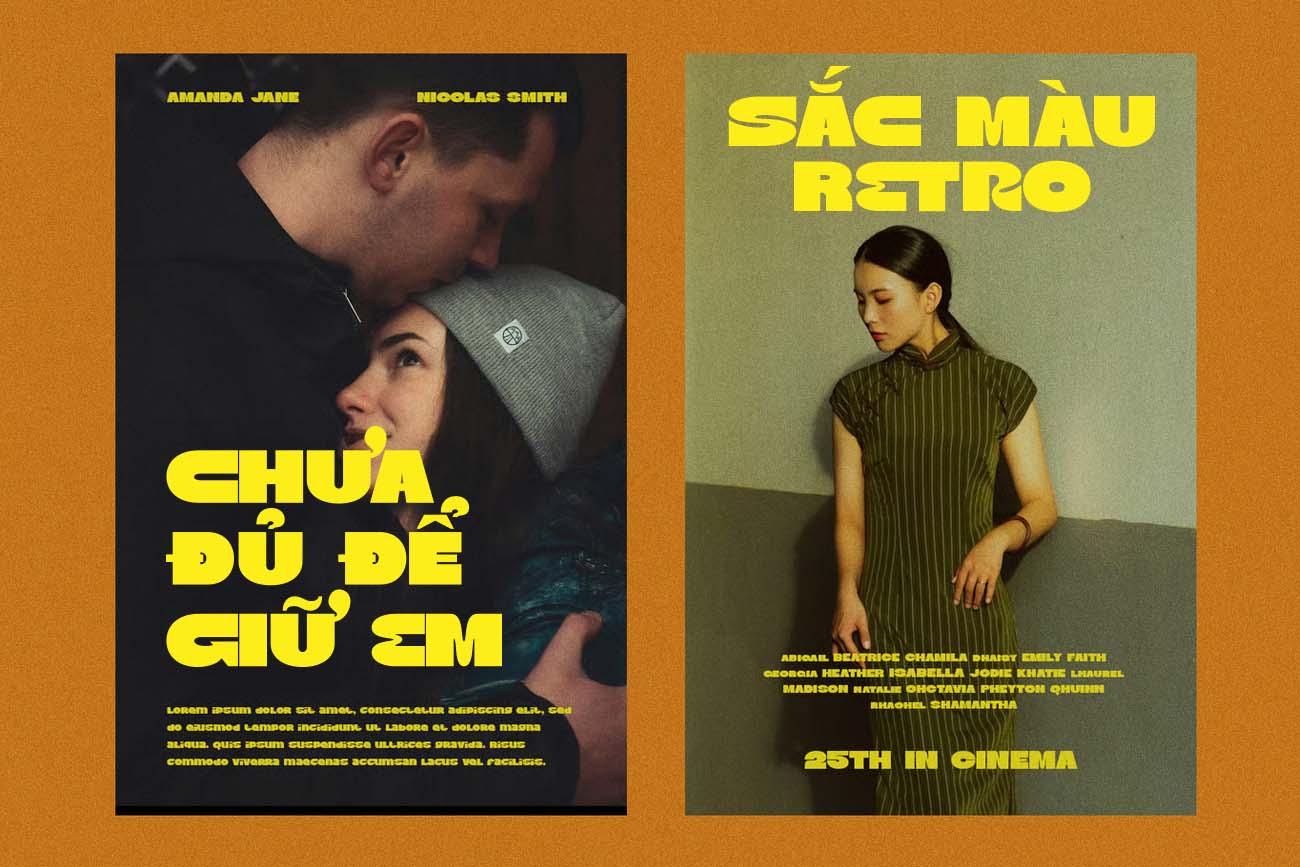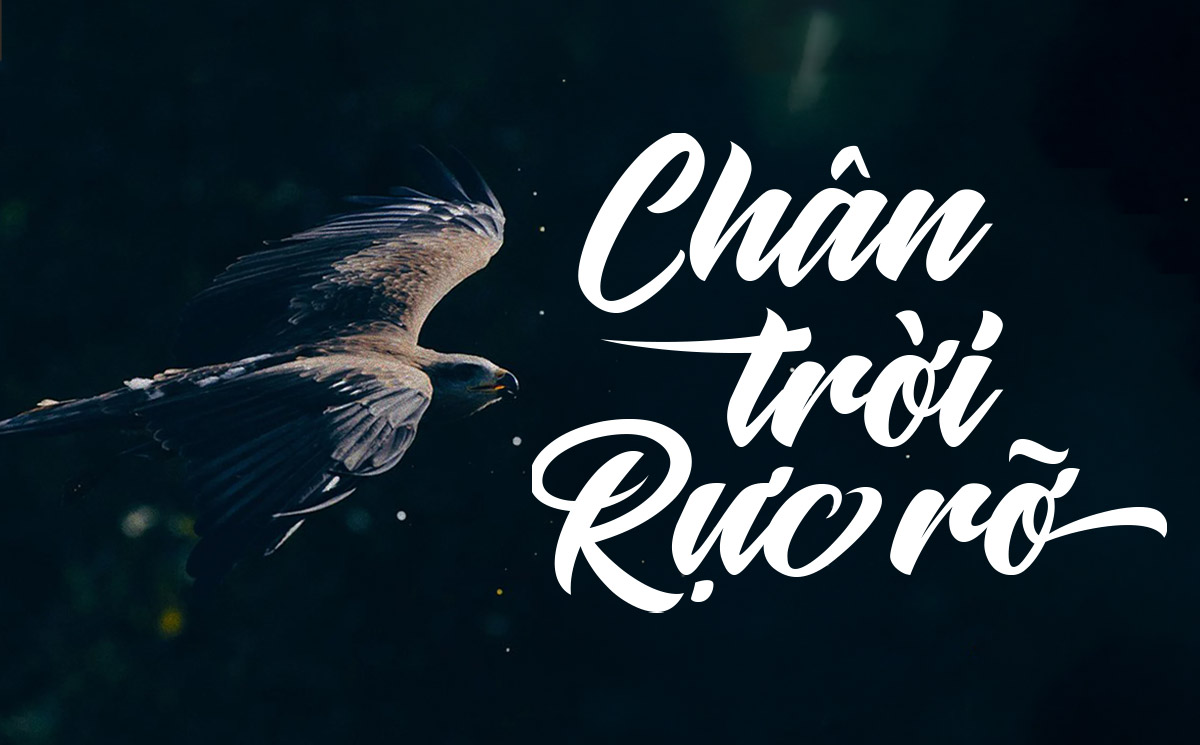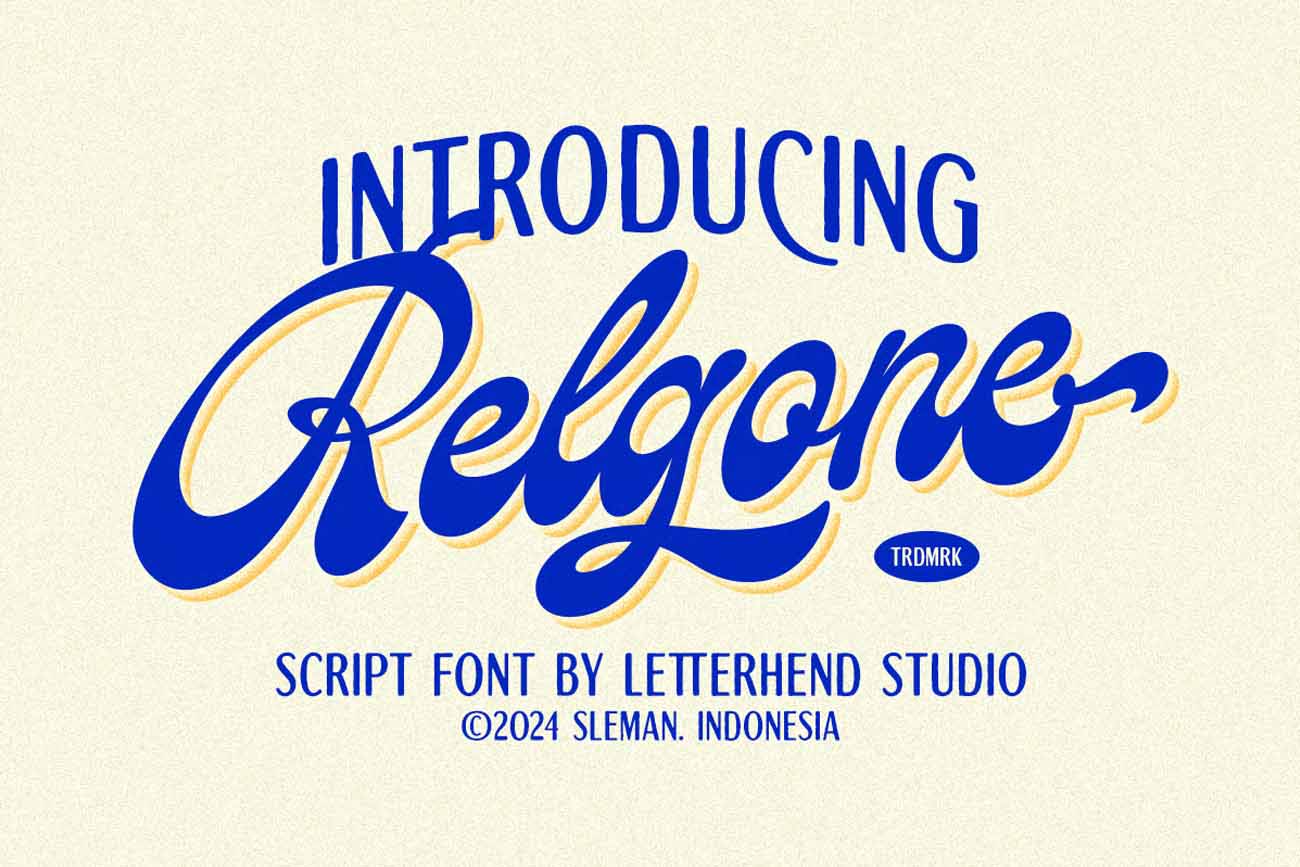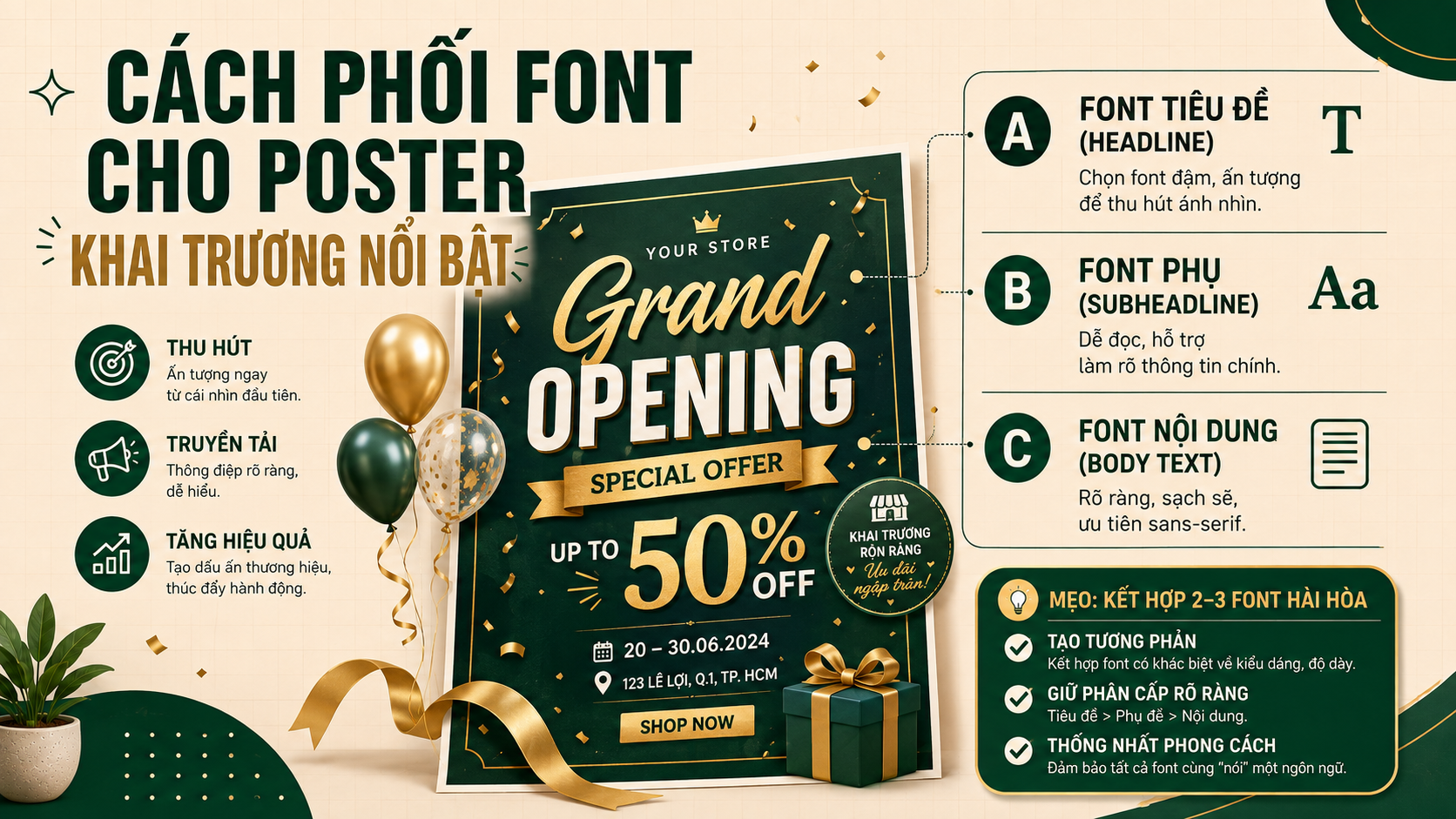
Font chữ cho sự kiện khai trương, grand opening và poster ưu đãi
Gợi ý 15 font TH Việt hóa nổi bật cho poster khai trương, grand opening, ưu đãi mở bán, banner sale opening và social post.
Poster khai trương cần tạo cảm giác “đang có chuyện vui diễn ra” ngay từ vài giây đầu. Khác với proposal hay catalogue, font cho grand opening không nhất thiết phải quá trung tính. Nó cần nổi bật, có khí thế, dễ đọc khi đặt trên nền đỏ, vàng, ảnh cửa hàng, ảnh sản phẩm hoặc các mảng ưu đãi lớn như “Mua 1 tặng 1”, “Giảm 50%”, “Tuần lễ khai trương”.
Bài viết này gợi ý 15 font TH Việt hóa khác nhóm font tài liệu doanh nghiệp gần đây, tập trung vào display, retro, brush, script và hoạt hình. Các font này phù hợp cho poster khai trương, banner grand opening, bài đăng social, backdrop sự kiện, biển treo cửa hàng và chương trình ưu đãi mở bán.
Chọn font khai trương cần chú ý gì?
Font khai trương phải làm tốt ba việc: thu hút, đọc nhanh và đúng không khí thương hiệu. Nếu cửa hàng là cafe retro, font hoài cổ sẽ hợp hơn font công nghệ. Nếu là showroom, gym hoặc cửa hàng thiết bị, font cứng cáp sẽ tạo cảm giác mạnh hơn. Nếu là tiệm bánh, trà sữa, kid shop, font tròn vui sẽ khiến poster dễ thương và gần gũi hơn.
Top font TH cho poster khai trương, grand opening và ưu đãi mở bán
1. TH Roge - poster grand opening kiểu retro, headline “Khai trương” và banner cửa hàng có cá tính
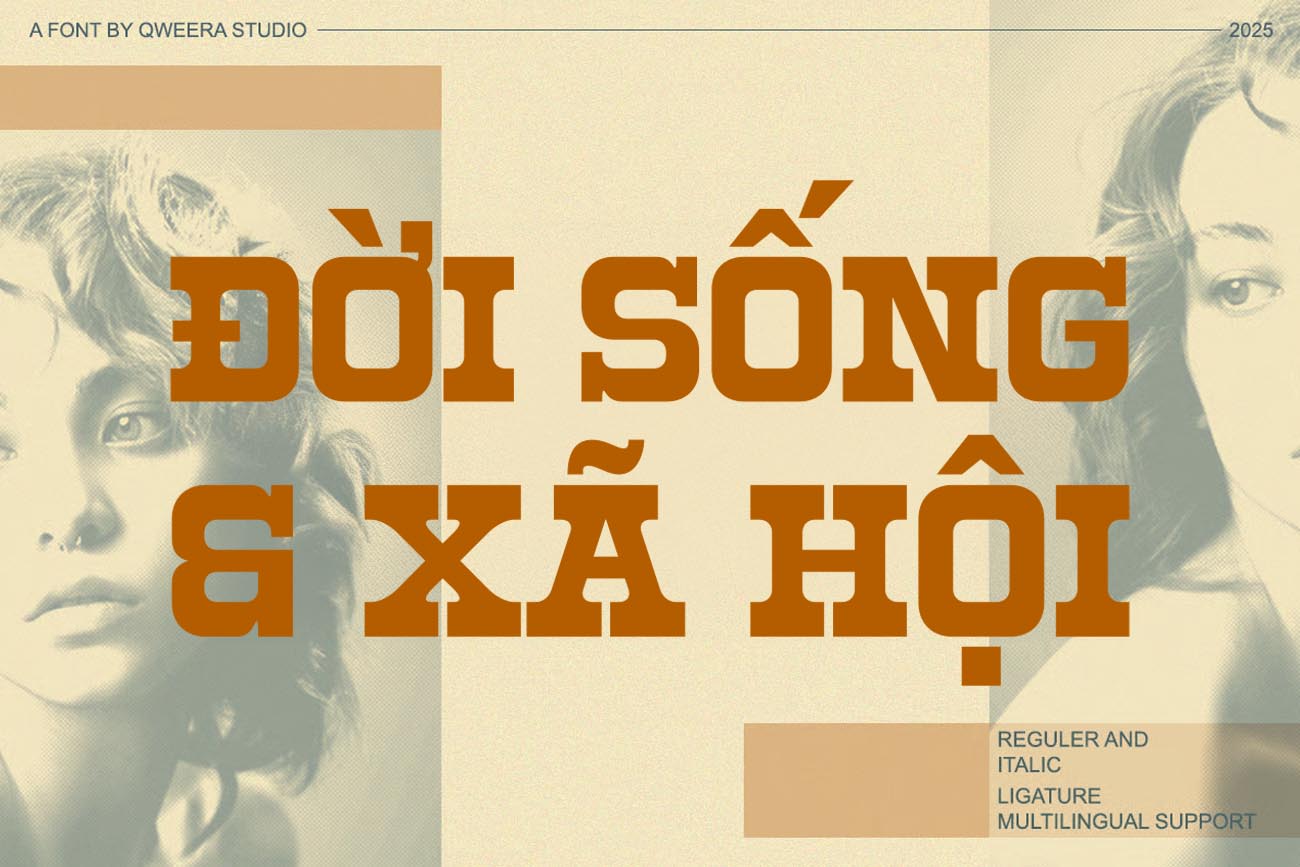
Tải font TH Roge nếu anh đang làm poster grand opening kiểu retro, headline “Khai trương” và banner cửa hàng có cá tính. Điểm mạnh của TH Roge là display retro nổi bật, dễ tạo cảm giác sự kiện có không khí và đáng ghé. Với poster khai trương, font này nên được thử trước trên các cụm chữ thật như “Khai trương hồng phát”, “Grand Opening”, “Ưu đãi mở bán”, “Giảm đến 50%” hoặc “Quà tặng 3 ngày đầu”.
Khi dùng TH Roge, anh nên giữ headline ngắn và mạnh. Các thông tin phụ như địa chỉ, thời gian, điều kiện ưu đãi, hotline nên dùng font sans-serif dễ đọc hơn để khách hàng không bỏ sót chi tiết quan trọng.
2. TH Acttime - poster ưu đãi mở bán, banner sale lớn và countdown khai trương
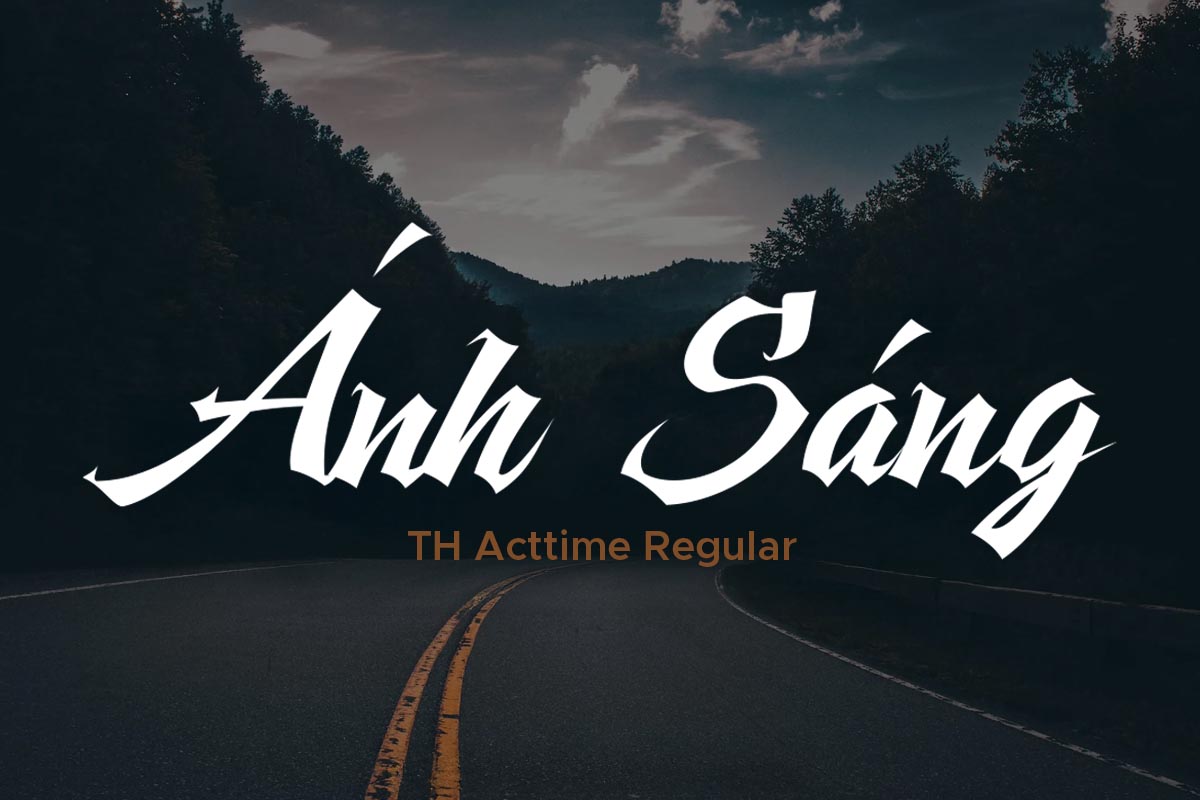
Tải font TH Acttime nếu anh đang làm poster ưu đãi mở bán, banner sale lớn và countdown khai trương. Điểm mạnh của TH Acttime là nét đậm, khỏe, giúp thông điệp giảm giá nhìn có lực hơn. Với poster khai trương, font này nên được thử trước trên các cụm chữ thật như “Khai trương hồng phát”, “Grand Opening”, “Ưu đãi mở bán”, “Giảm đến 50%” hoặc “Quà tặng 3 ngày đầu”.
Khi dùng TH Acttime, anh nên giữ headline ngắn và mạnh. Các thông tin phụ như địa chỉ, thời gian, điều kiện ưu đãi, hotline nên dùng font sans-serif dễ đọc hơn để khách hàng không bỏ sót chi tiết quan trọng.
3. TH Throwback Glorious - thiết kế khai trương phong cách vintage, poster quán cafe và shop lifestyle
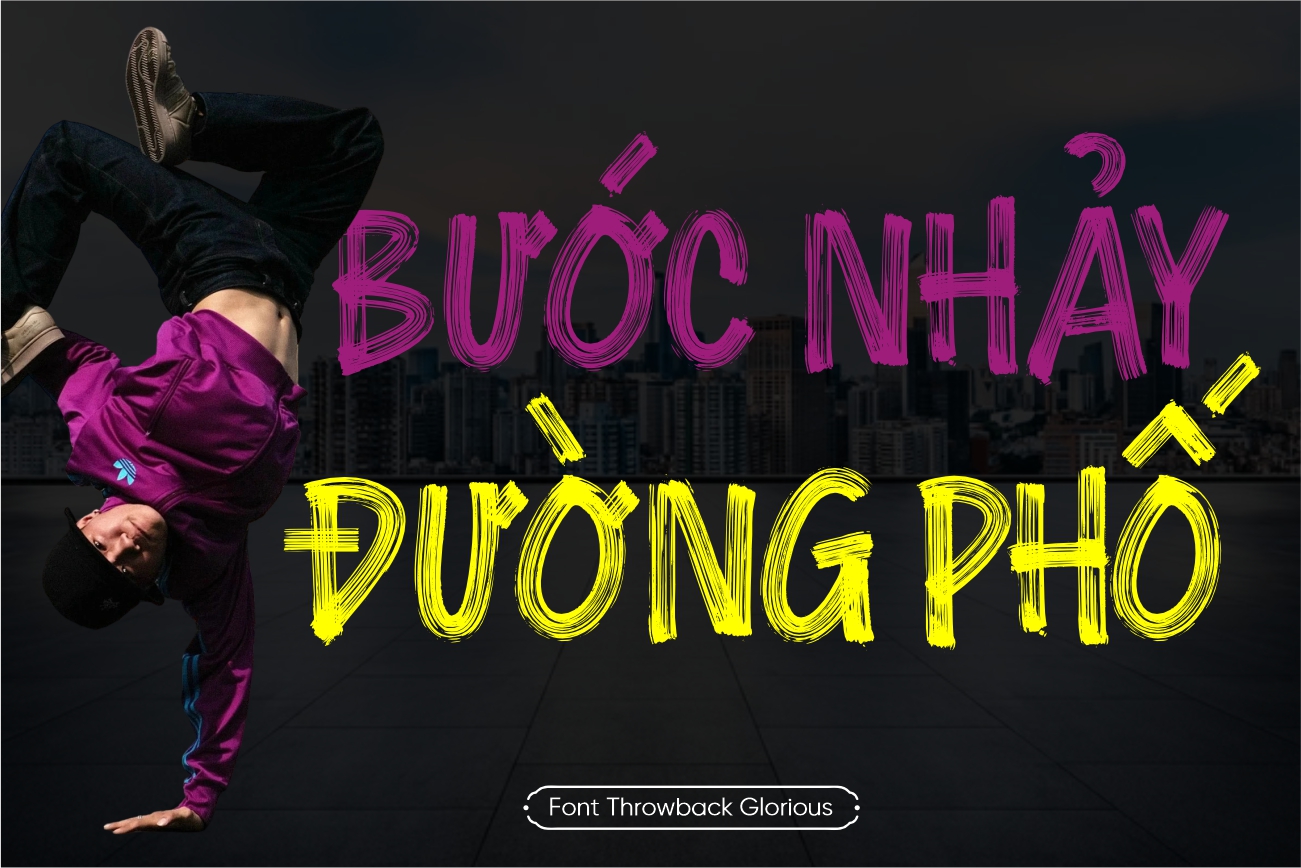
Tải font TH Throwback Glorious nếu anh đang làm thiết kế khai trương phong cách vintage, poster quán cafe và shop lifestyle. Điểm mạnh của TH Throwback Glorious là tạo cảm giác hoài cổ, hợp với thương hiệu muốn khác biệt khỏi kiểu sale thông thường. Với poster khai trương, font này nên được thử trước trên các cụm chữ thật như “Khai trương hồng phát”, “Grand Opening”, “Ưu đãi mở bán”, “Giảm đến 50%” hoặc “Quà tặng 3 ngày đầu”.
Khi dùng TH Throwback Glorious, anh nên giữ headline ngắn và mạnh. Các thông tin phụ như địa chỉ, thời gian, điều kiện ưu đãi, hotline nên dùng font sans-serif dễ đọc hơn để khách hàng không bỏ sót chi tiết quan trọng.
4. TH Tan Meringue - banner opening cho tiệm bánh, quán đồ uống, local brand và sự kiện ra mắt bộ sưu tập
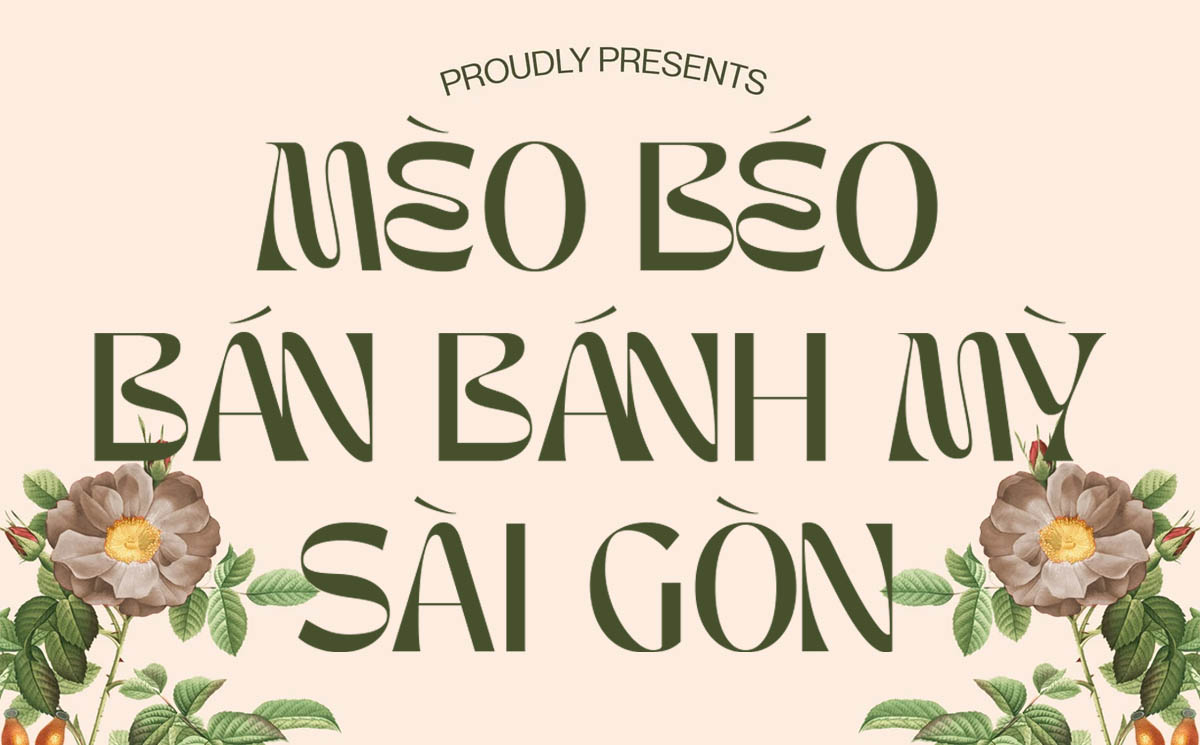
Tải font TH Tan Meringue nếu anh đang làm banner opening cho tiệm bánh, quán đồ uống, local brand và sự kiện ra mắt bộ sưu tập. Điểm mạnh của TH Tan Meringue là display retro vui mắt, đủ mềm để tạo cảm giác thân thiện. Với poster khai trương, font này nên được thử trước trên các cụm chữ thật như “Khai trương hồng phát”, “Grand Opening”, “Ưu đãi mở bán”, “Giảm đến 50%” hoặc “Quà tặng 3 ngày đầu”.
Khi dùng TH Tan Meringue, anh nên giữ headline ngắn và mạnh. Các thông tin phụ như địa chỉ, thời gian, điều kiện ưu đãi, hotline nên dùng font sans-serif dễ đọc hơn để khách hàng không bỏ sót chi tiết quan trọng.
5. TH Neue Yokarto - poster khai trương cửa hàng thời trang, salon, boutique và showroom nhỏ
Tải font TH Neue Yokarto nếu anh đang làm poster khai trương cửa hàng thời trang, salon, boutique và showroom nhỏ. Điểm mạnh của TH Neue Yokarto là retro cổ điển nhưng vẫn dễ dùng cho headline ngắn. Với poster khai trương, font này nên được thử trước trên các cụm chữ thật như “Khai trương hồng phát”, “Grand Opening”, “Ưu đãi mở bán”, “Giảm đến 50%” hoặc “Quà tặng 3 ngày đầu”.
6. TH Manthone - poster khuyến mãi, biển treo khai trương và social post mở bán
Font chữ cho khai trương cần vui, nổi bật và dễ đọc, nhưng vẫn phải đúng tính cách thương hiệu. Nhóm font TH trong bài này đi theo hướng khác hẳn các font tài liệu doanh nghiệp: giàu không khí sự kiện hơn, nhiều display/retro/brush hơn và hợp với poster ưu đãi hơn.
Khi chọn font cuối cùng, hãy đặt thử vào đúng layout khai trương: ảnh cửa hàng, màu thương hiệu, khung ưu đãi, ngày giờ và CTA. Nếu khách hàng chỉ nhìn 3 giây vẫn hiểu chương trình, đọc được thông tin chính và cảm thấy muốn ghé, font đó đã làm đúng việc của nó.